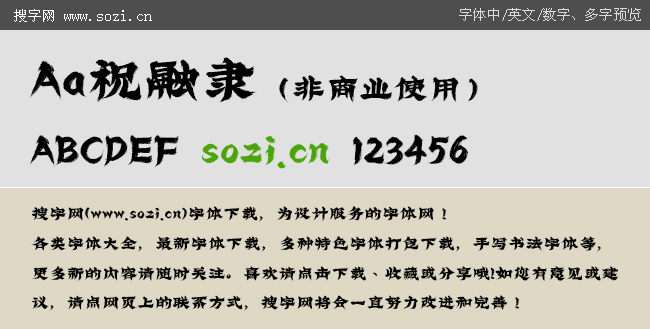
Aa祝融隸
搜字網(wǎng)給大家提供一款A(yù)a祝融隸(非商業(yè)使用)中文字體下載,Aa祝融隸是一款手寫風(fēng)格的書法字體,該字體筆畫隨性灑脫,以隸書扁寬穩(wěn)定的結(jié)構(gòu)為基礎(chǔ),配以尖銳出鋒的板繪筆形,風(fēng)格肆意動感。適合應(yīng)用于海報設(shè)計、包裝設(shè)計、網(wǎng)頁設(shè)計等應(yīng)用(此字體為個人非商用版,商用可以聯(lián)系QQ:1006760504)。